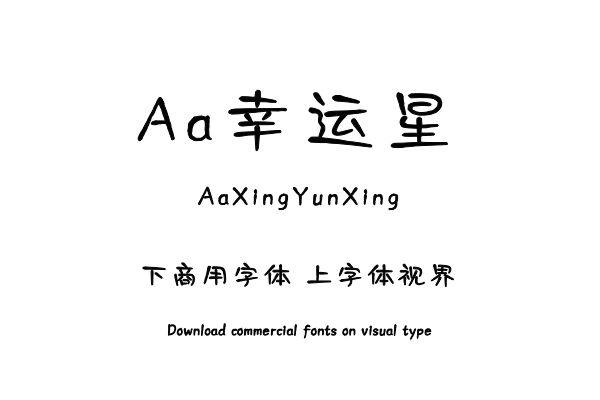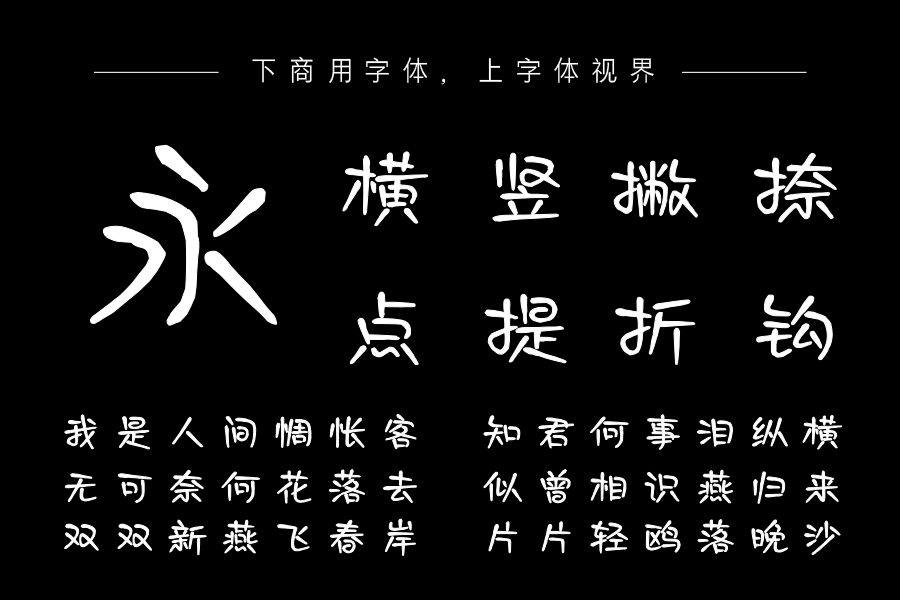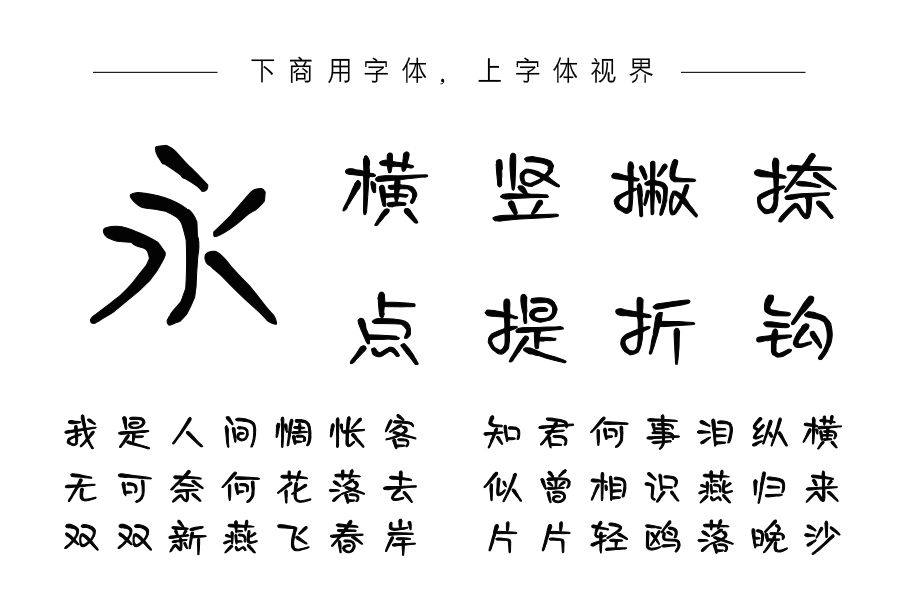
本字体是由轮廓不规则的数码笔刷制作,笔画向四角放射减细,形成不规则星形,一些笔画采用连笔处理,俏皮可爱,笔画在外放的大规则下呈现随性错落的分布,趣味十足。购买须知:“下载服务费”与“字体VIP”所获得字体 仅用于个人非商用, 商用请联系付费授权。本字体为电脑用字,手机没有root权限不支持直接手机换字(手机如何root,请自行百度搜索教程)。购买前请先 了解清楚后再付款 ,字体为虚拟产品无法回收 一旦购买不支持退款。